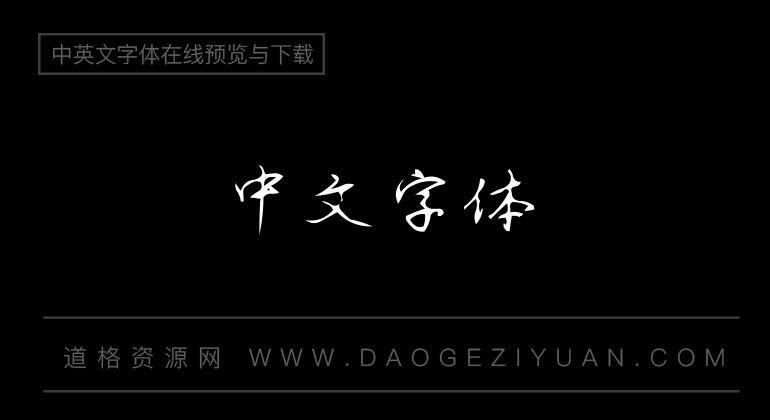
博洋规范字3500是一款精心设计的中文字体,它由国家新闻出版广电总局精心设计,被称为“中国最具影响力的字体”。它融合了中国传统文化的美感,同时又具有现代感,是一款极具艺术性的文字。它具有良好的可读性和可辨识性,可以有效地提高文字的清晰度和美观性,更容易被读者接受。博洋规范字3500的字体设计受到了众多设计师的赞誉,是一款实用性极强的文字字体。文件名:BoYangGuiFanZi3500-1.ttf
博洋规范字3500是一款非常不错的手写艺术字体,具有很好的视觉感,适合于文化类的宣传设计、商业类品牌的广告和产品包装设计以及个性化文字排版等较多场景。